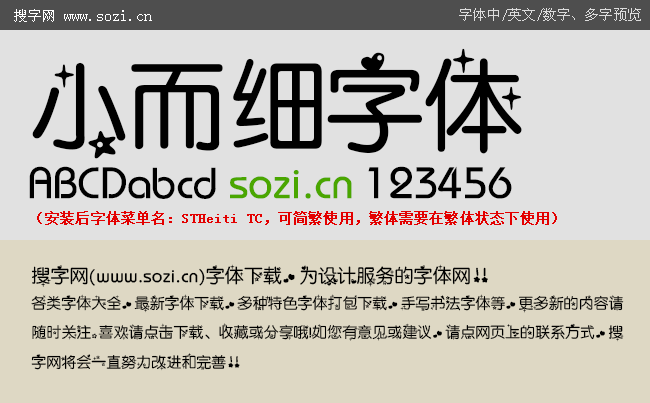
小而細(xì)字體
搜字網(wǎng)給大家提供一款小而細(xì)字體手機(jī)中文字體下載。這款手機(jī)字體是以圓體字體為原形,筆畫間嵌入了可愛的卡通圖案。在具備圓字體清晰端正的風(fēng)格同時,卡通味也特別濃,是一款非常可愛的卡通字體,特別適合喜歡手機(jī)字體個性一些的朋友在手機(jī)上安裝使用。